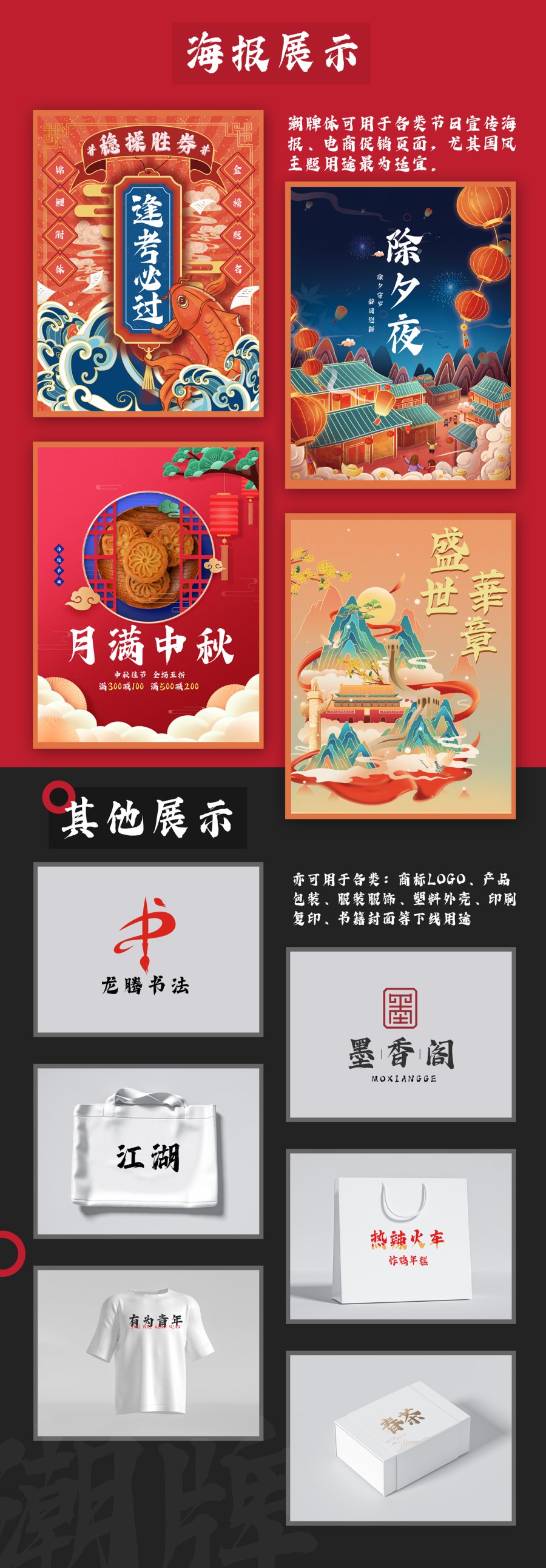
海报展示中的毛笔书法字体
毛笔字在设计中是最容易出彩的设计手法,很多海报和宣传画册,都可以看到毛笔书法字体的身影,有了毛笔字的加持,瞬间能够使页面增彩很多。
例如:这款印品潮牌体,笔画饱满浑厚、又不失刚劲,使得整体表面风格内敛,实际上藏锋于内,笔画之间的承启转合,潇洒流畅。可用于传统节日海报宣传、影视媒体、产品包装等多种场景之中。
印品潮牌体